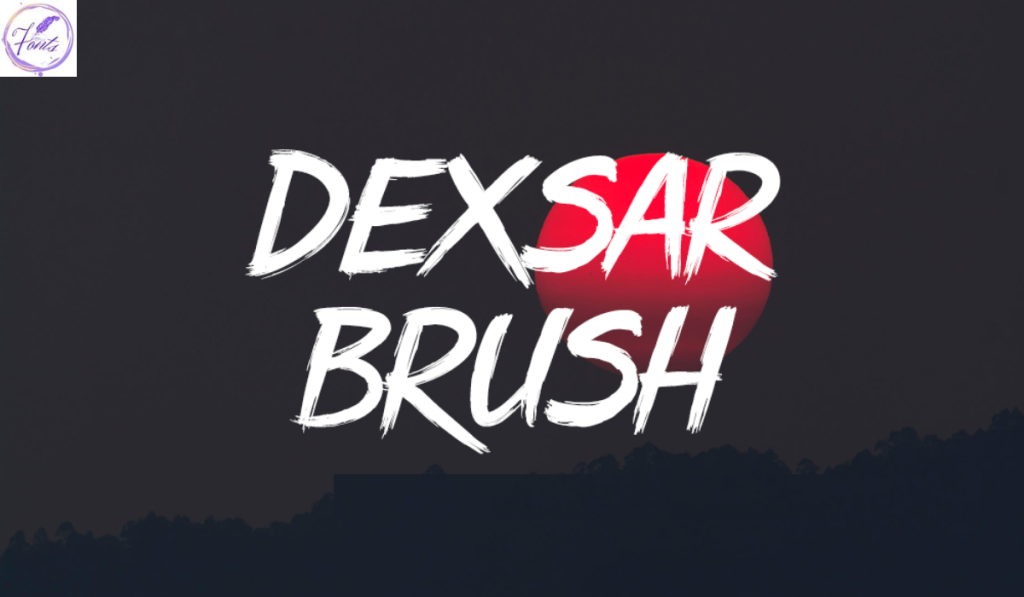
Font chữ nét cọ việt hóa
Phân loại: Cá tính, Độc đáo, Vui nhộn, Trẻ trung
Kiểu chữ: Kiểu chữ viết tay (brush)
Độ dày: Regular, Bold
Font chữ nét cọ là một bộ font độc đáo, được thiết kế để mô phỏng các nét vẽ bằng cọ. Được phát triển bởi một nhóm nhà thiết kế tài năng, font này ra mắt vào năm 2022 và nhanh chóng trở thành lựa chọn phổ biến cho các dự án thiết kế nghệ thuật và sáng tạo. Font chữ nét cọ mang lại sự mềm mại và tự nhiên cho các văn bản, giúp chúng trở nên sống động và thu hút hơn. Phiên bản Việt hóa của font chữ nét cọ giúp người dùng Việt Nam dễ dàng sử dụng trong các văn bản tiếng Việt, tạo nên những sản phẩm độc đáo và ấn tượng.
Đánh giá font chữ nét cọ
Font chữ nét cọ nhận được nhiều đánh giá tích cực từ cộng đồng thiết kế nhờ vào sự sáng tạo và linh hoạt của nó. Các nhà thiết kế đánh giá cao font này bởi sự tự nhiên và mềm mại trong từng nét chữ, tạo nên cảm giác như đang vẽ bằng tay thực sự. Font chữ nét cọ rất phù hợp cho các dự án nghệ thuật, thiệp mời, poster và các sản phẩm cần sự sáng tạo. Phiên bản Việt hóa của font này không chỉ giữ nguyên được phong cách độc đáo của bản gốc mà còn bổ sung đầy đủ các ký tự tiếng Việt, giúp người dùng thoải mái sáng tạo.